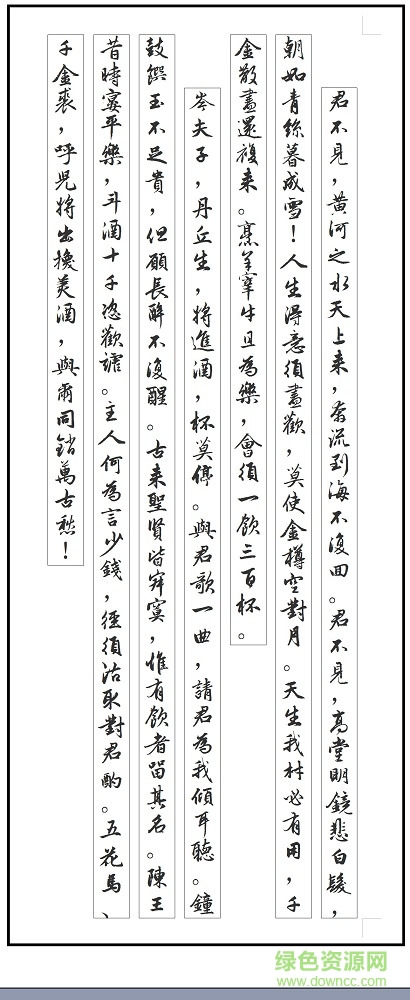
字酷堂南元松雪行書(shū)是字庫(kù)堂全新推出的一款行書(shū)字體,字體大氣磅礴、氣勢(shì)威嚴(yán),不失行書(shū)的流暢灑脫,又有著獨(dú)特的娟秀端莊美,喜歡的朋友不妨來(lái)綠色資源網(wǎng)體驗(yàn)吧!
字酷堂南元松雪行書(shū),支持中文繁簡(jiǎn)體,包含繁字字形七千余字,整體融合了行書(shū)靈活流動(dòng)之氣,和獨(dú)特的大氣灑脫韻味。
南元松雪行書(shū)一說(shuō)是趙孟頫趙體,因趙孟頫號(hào)松雪道人。
趙體楷書(shū)用筆沉穩(wěn),章法分明,外貌圓潤(rùn)而筋骨內(nèi)涵,其點(diǎn)畫(huà)華滋遒勁,結(jié)體寬綽秀美,平中寓險(xiǎn),點(diǎn)畫(huà)之間呼應(yīng)十分緊密。,趙體楷書(shū)既保留了唐楷的法度,又不拘泥于唐楷的一招一式,在楷書(shū)中經(jīng)常有一些生動(dòng)俊俏的行書(shū)筆法與結(jié)構(gòu),筆劃形態(tài)生動(dòng)自然,趙體楷書(shū)被譽(yù)之為活的楷書(shū);而趙體行書(shū)溫潤(rùn)閑雅,輕盈流動(dòng);筆法精致秀美充滿了書(shū)卷氣與富貴氣。其“書(shū)法以用筆為上,而結(jié)字亦須用工。蓋結(jié)字因時(shí)相傳,用筆千古不易?!币殉蔀榍Ч琶?。